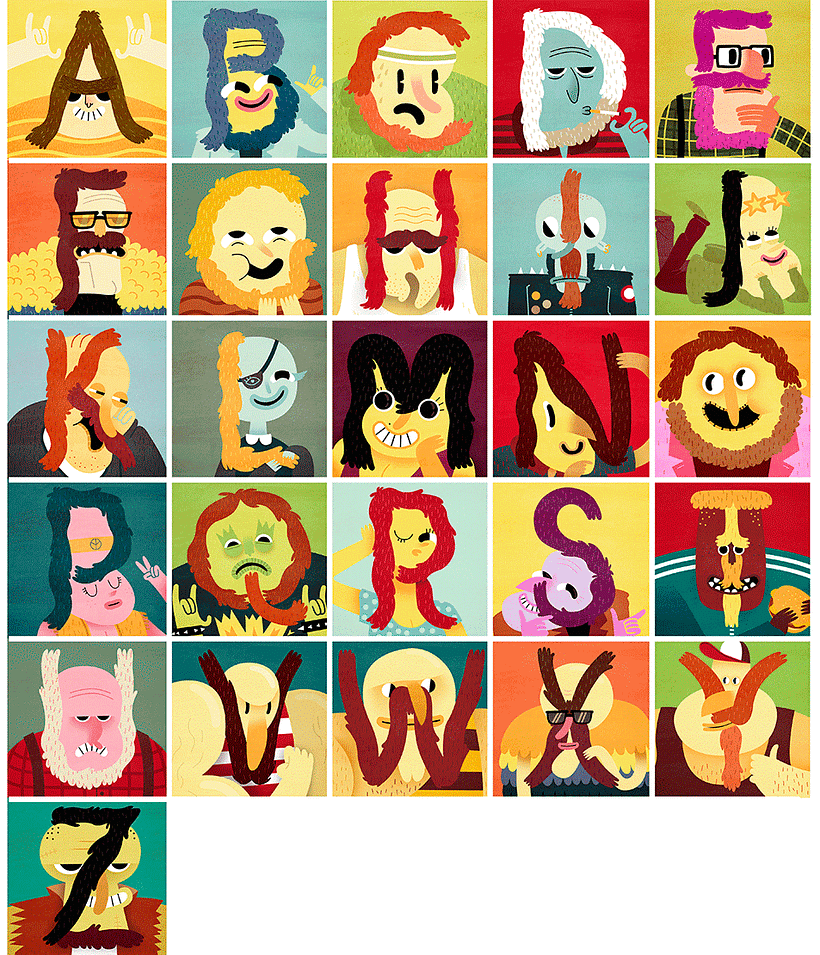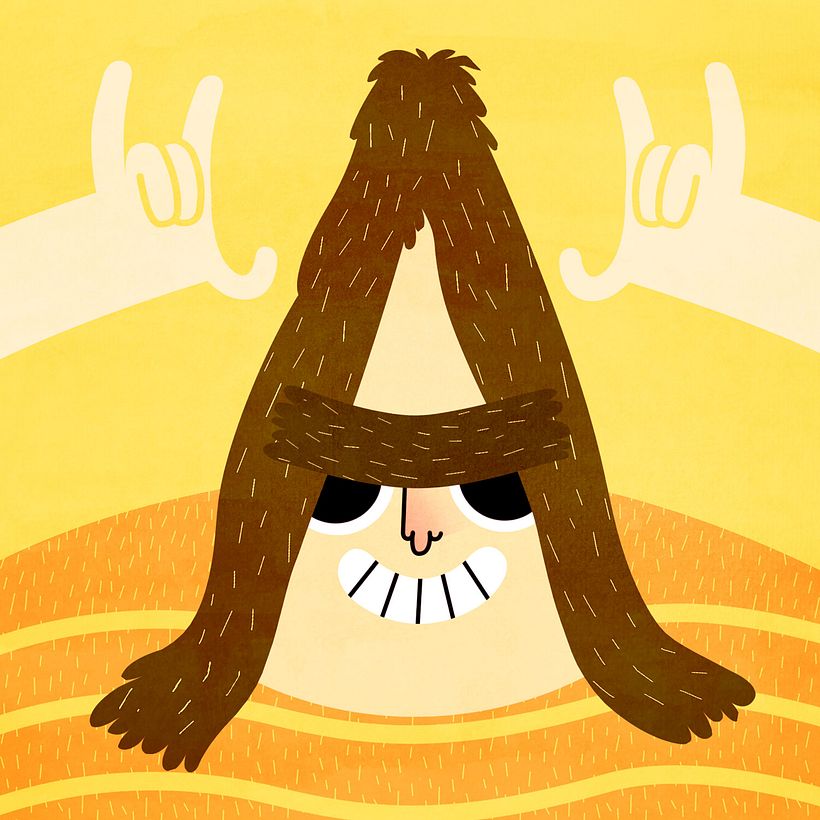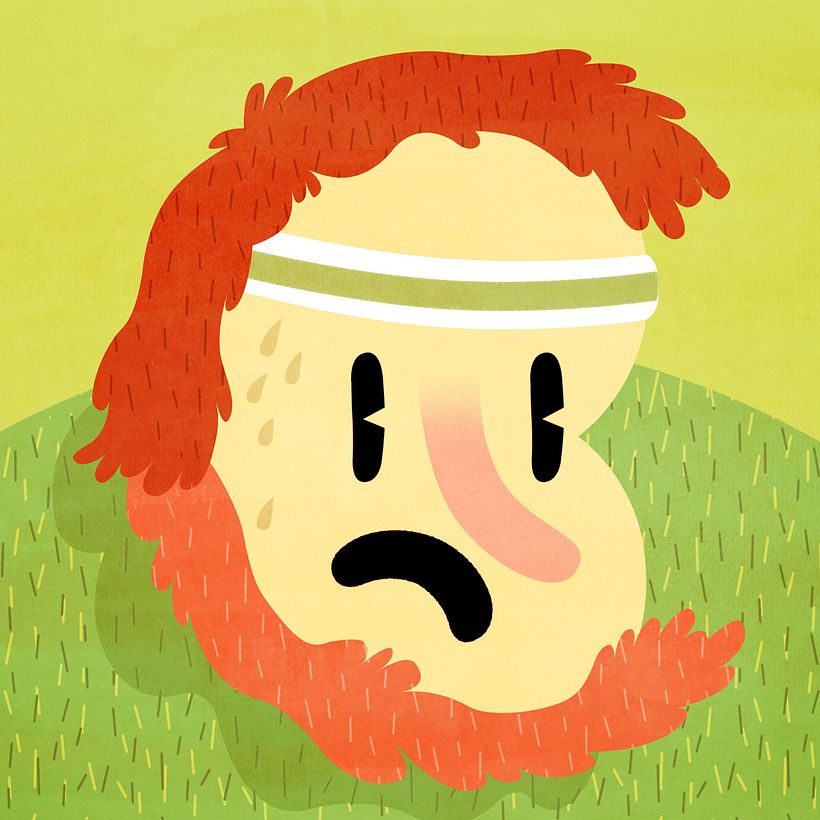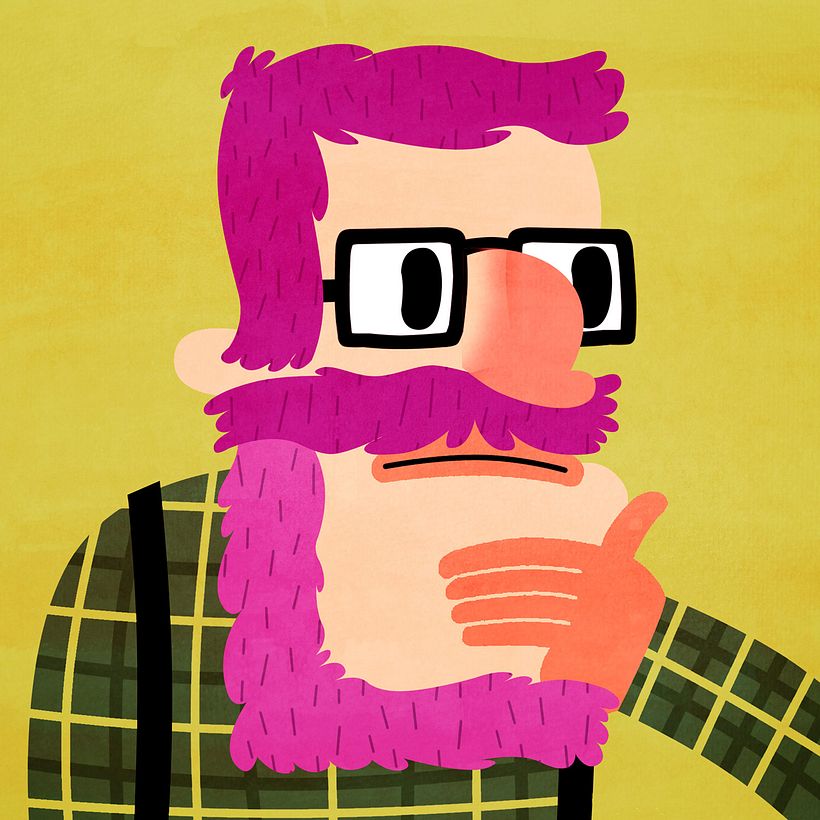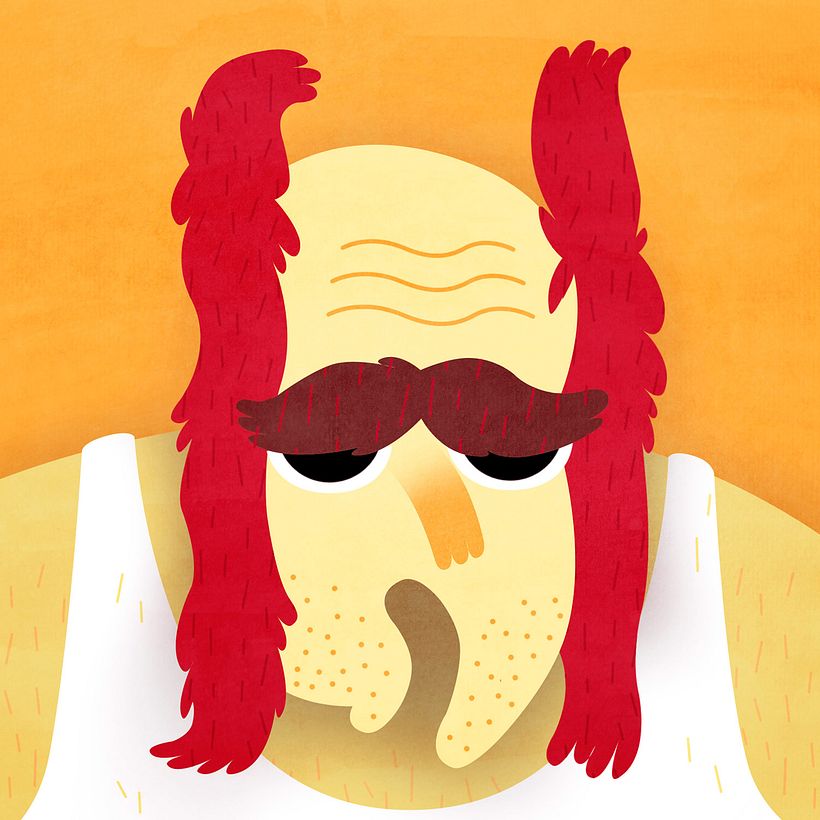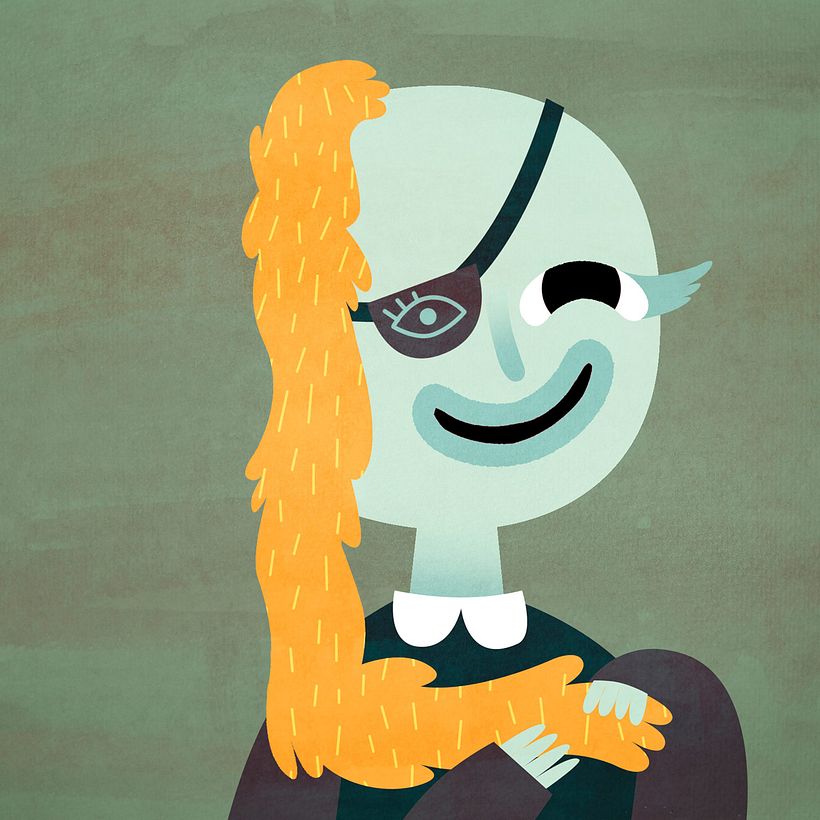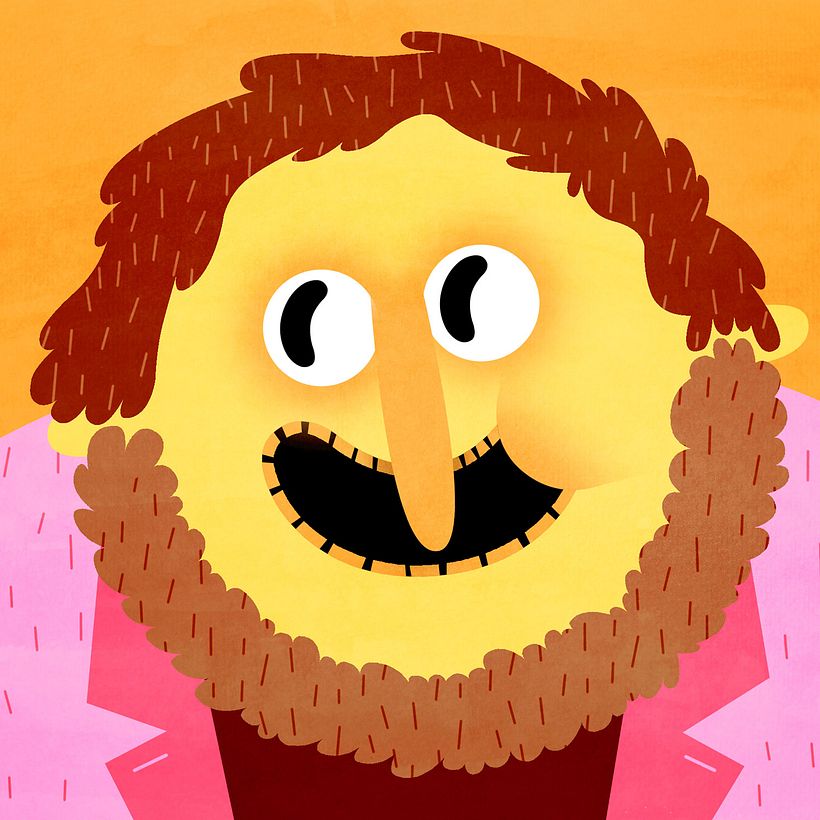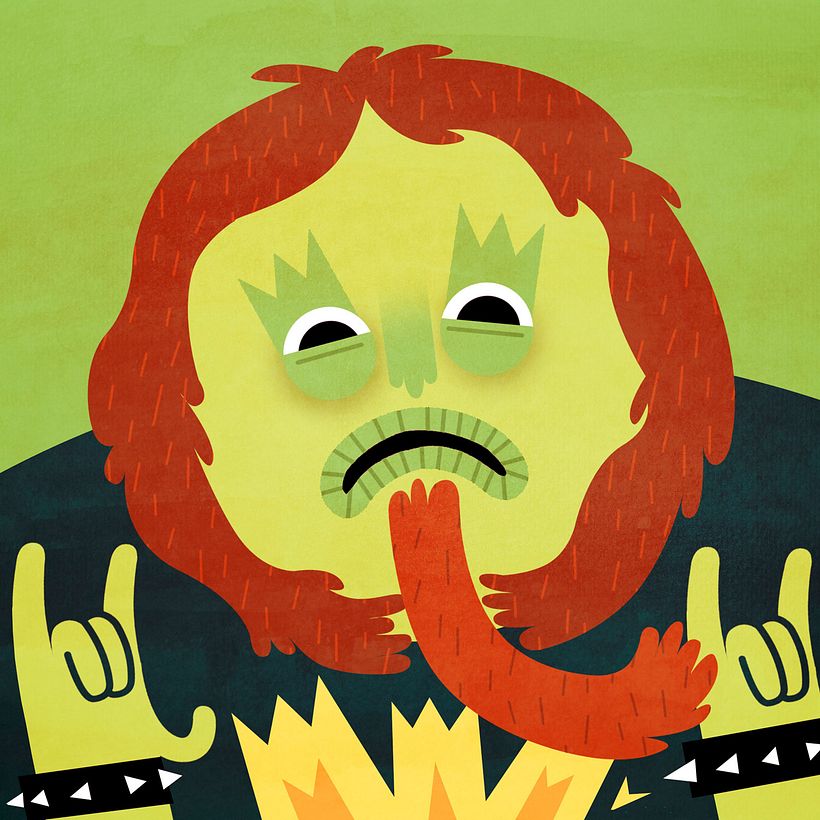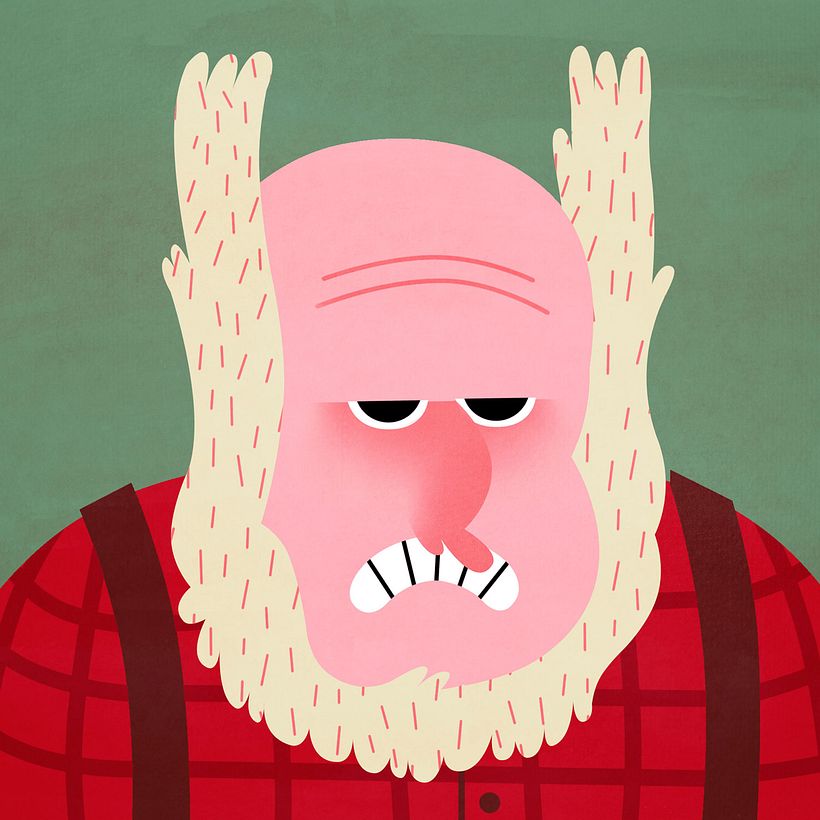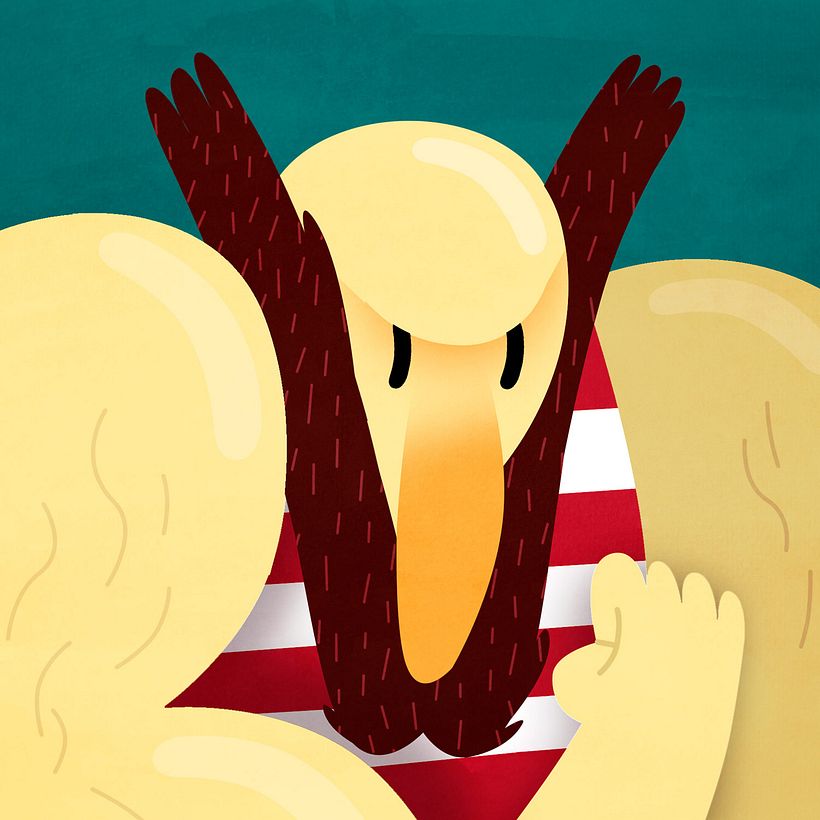
Pelotipo, una tipografía por los pelos
Uniendo barbas, bigotes, cejas y peinados imposibles, Dani Blanc crea un alfabeto peludo de lo más divertido y original.
Si algo tiene la maravillosa iniciativa de 36 Days of Type es que deja tras de sí una resaca creativa que dura semanas, meses, ¡años! Durante poco más de un mes, una vez al año, diseñadores, ilustradores y artistas de todo el mundo publican al unísono sus diseños tipográficos y las redes sociales se inundan de letras. El 'Pelotipo' de Dani Blanc (@dani_blanc) es un buen ejemplo de ello.
Recreándose en la morfología, el vello facial y en los peinados estrambóticos, el diseñador español ha creado su propio y original abecedario capilar en el que cada día y cada letra tiene como protagonista a un personaje peludo.
Pelotipo fue la propuesta que Dani Blanc realizó para la segunda edición de 36 Days of Type. El resultado son 26 divertidos retratos (el diseñador no se atrevió con los números en esta edición) en los que la tipografía, la ilustración, el color y el humor confluyen en uno de los proyectos más divertidos que hemos visto en la convocatoria.